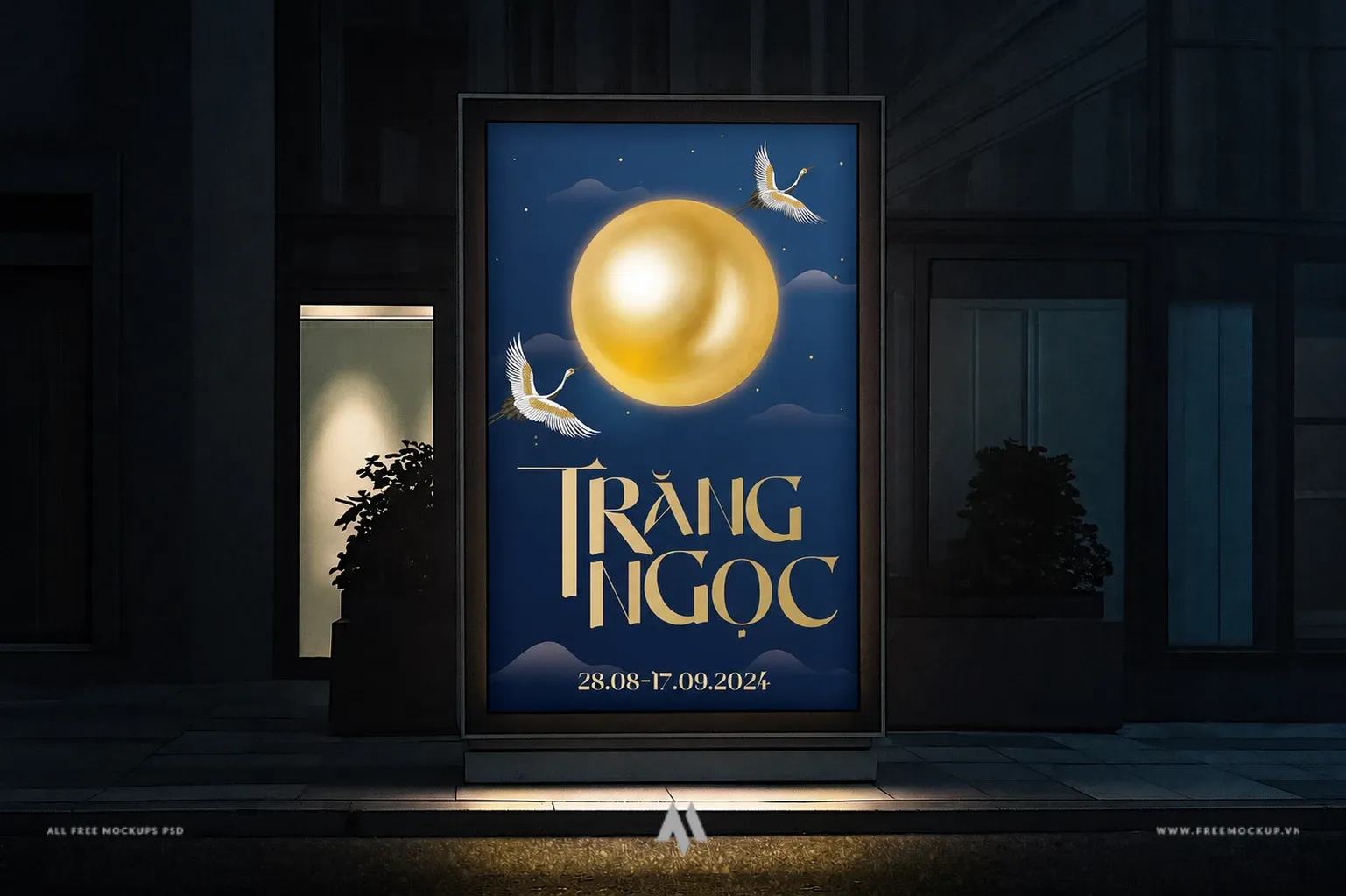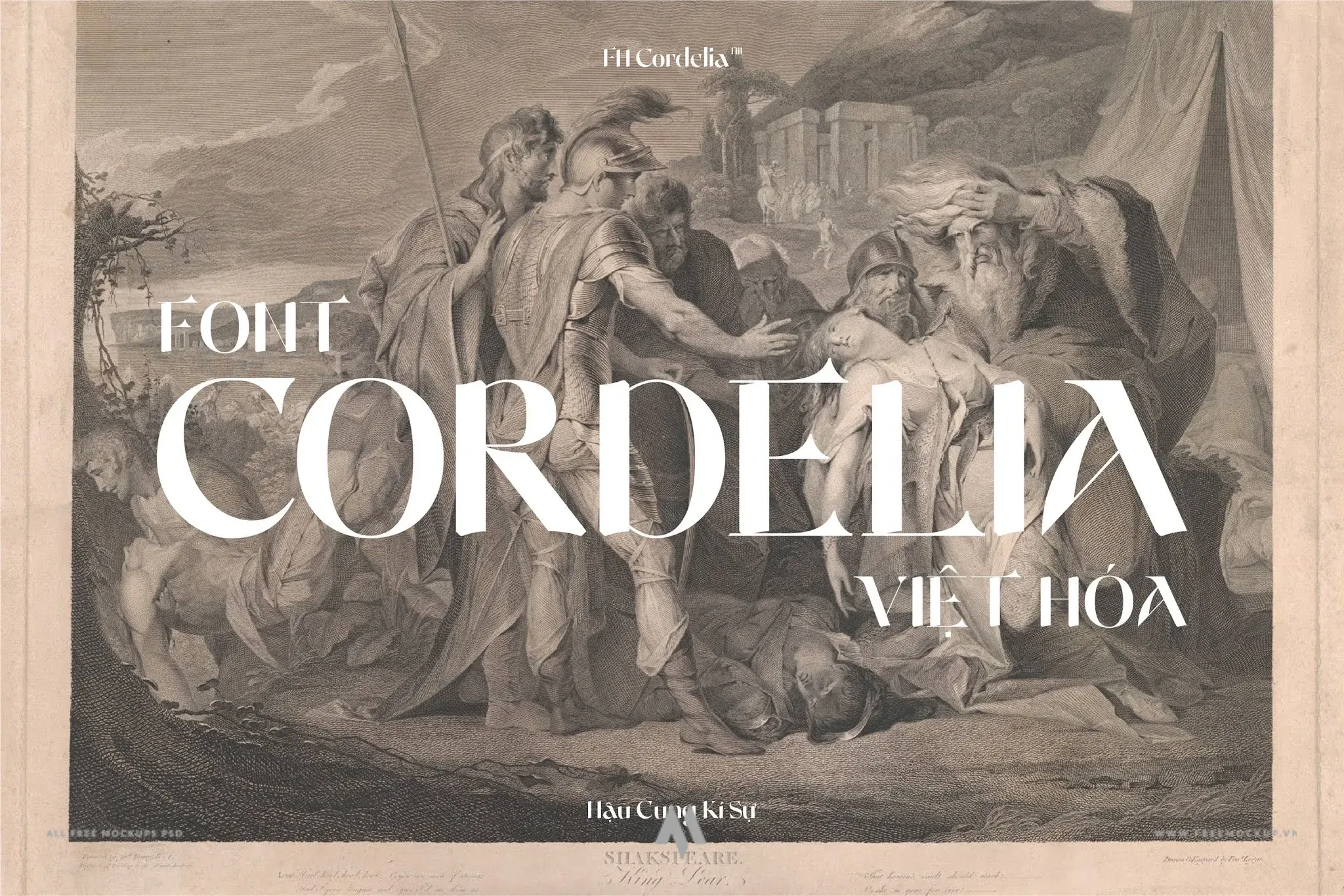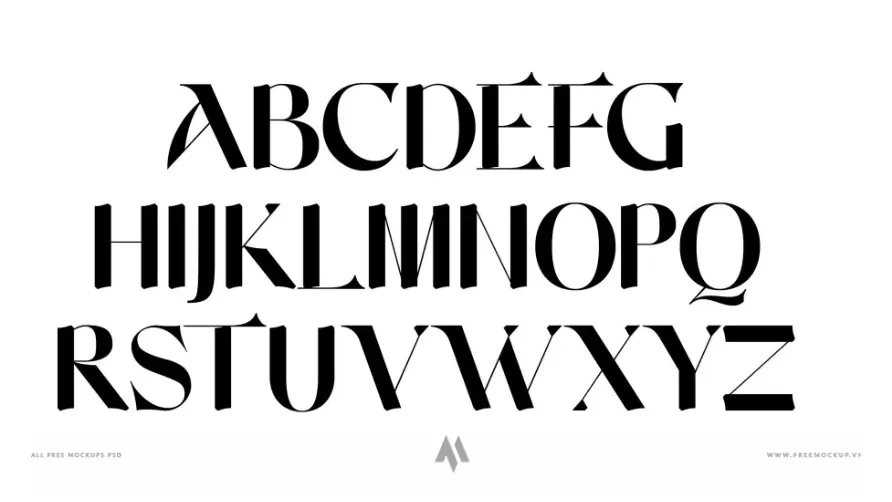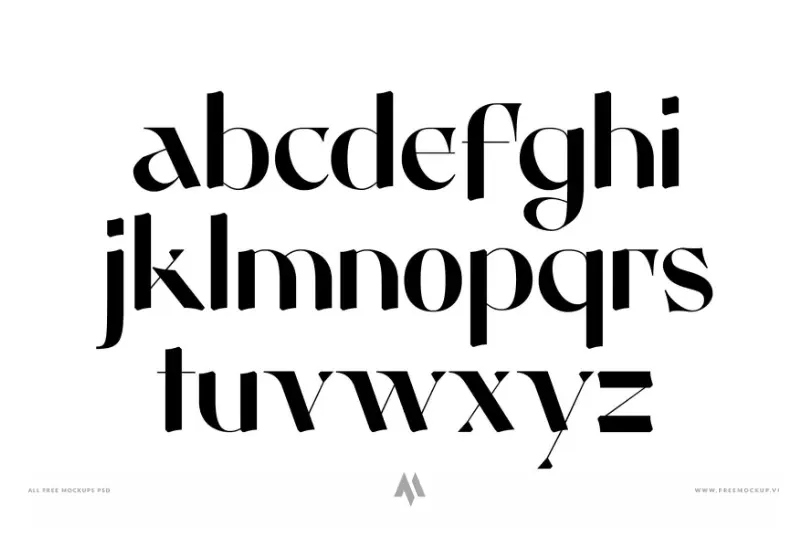
Font FH Cordelia Việt Hóa là bộ font chữ hiển thị mang âm hưởng thư pháp phương Đông độc đáo, dung hòa khéo léo giữa nét đẹp truyền thống và ngôn ngữ thiết kế hiện đại. Với cấu trúc chữ cá tính cùng các chi tiết gập đầu nét tinh xảo, bộ font tạo nên ấn tượng thị giác mạnh mẽ, sâu lắng và đậm chất nghệ thuật cho các ấn phẩm đương đại.
Đặc điểm nổi bật
- Nguồn cảm hứng Á Đông tinh tế: Các nếp gấp và điểm nhấn ở đầu ngọn chữ mô phỏng nét bút lông truyền thống, tạo nên phong thái phương Đông trang nhã và bí ẩn.
- Cấu trúc chữ độc đáo & Đa dạng độ dày: Sự phối hợp hài hòa giữa chữ in hoa và chữ thường cùng 2 định dạng độ dày (weights) khác nhau, giúp linh hoạt biến hóa bố cục tiêu đề.
- Tỉ mỉ trong từng chi tiết: Từng đường nét nhỏ được trau chuốt sắc sảo, tôn lên cá tính riêng biệt mà vẫn đảm bảo tính hiện đại, dễ ứng dụng.
- Chuẩn hóa tiếng Việt đầy đủ: Bộ dấu tiếng Việt được tinh chỉnh hài hòa, tương thích mượt mà trên các công cụ thiết kế phổ biến như Adobe Photoshop, Illustrator, InDesign, Figma và Canva.
Ứng dụng hoàn hảo trong thiết kế
- Nhận diện thương hiệu: Thiết kế logo, bảng hiệu cho trà đạo, ẩm thực Á Đông, thời trang cổ phong, khu nghỉ dưỡng văn hóa và spa phong cách thiền.
- Xuất bản & Biên tập: Bìa sách văn học, tiểu thuyết lịch sử, thơ ca, tạp chí nghệ thuật và ấn phẩm nghiên cứu văn hóa.
- Bao bì & Nhãn mác: Bao bì trà, gốm sứ, hộp bánh trung thu, nhãn mác sản phẩm thảo mộc và quà tặng truyền thống cao cấp.
- Truyền thông & Sự kiện: Áp phích (poster) triển lãm, banner sự kiện nghệ thuật, visual phim điện ảnh và bài đăng truyền thông trên mạng xã hội.